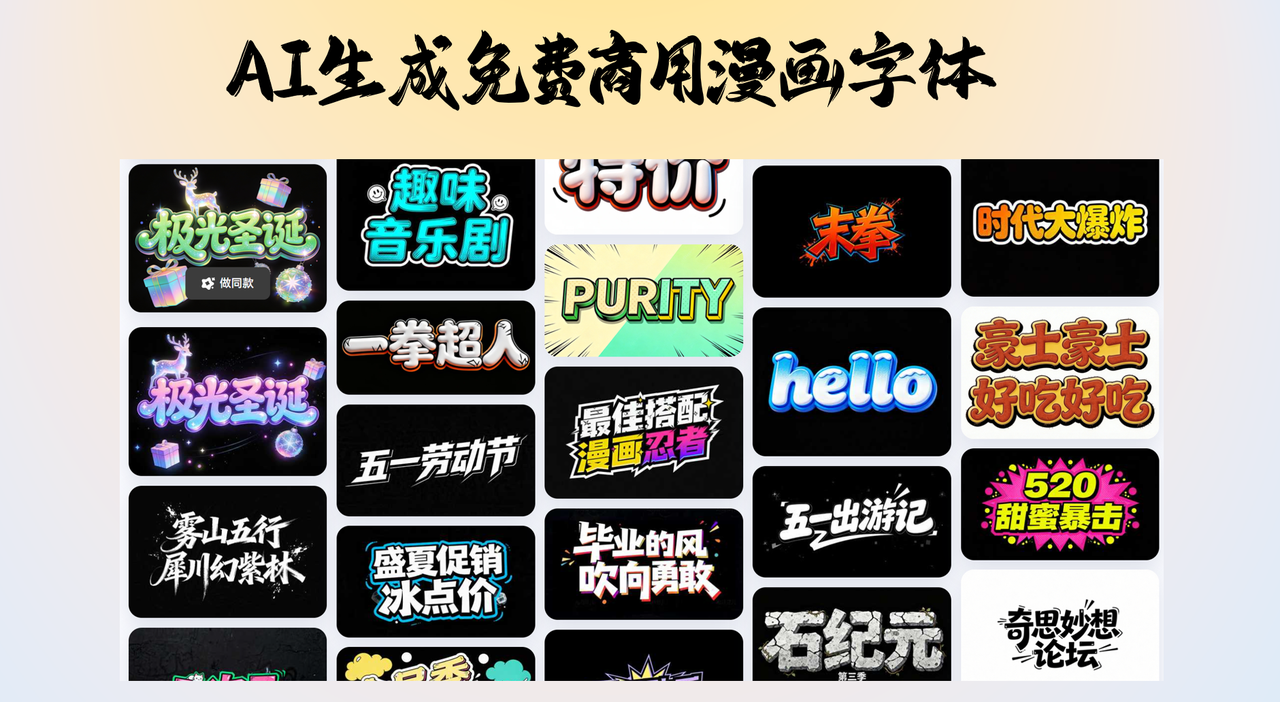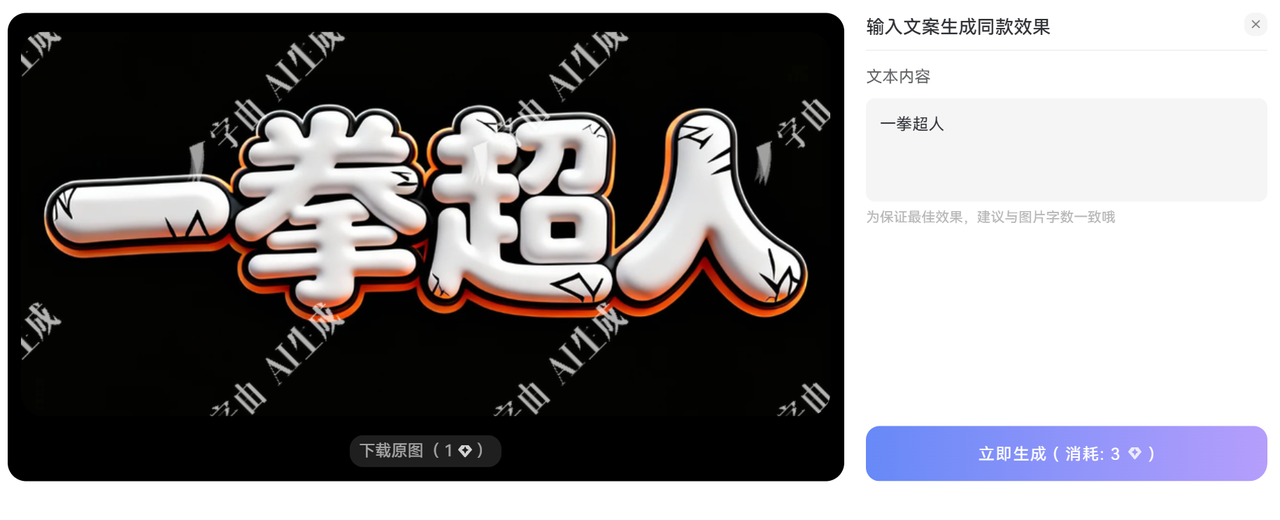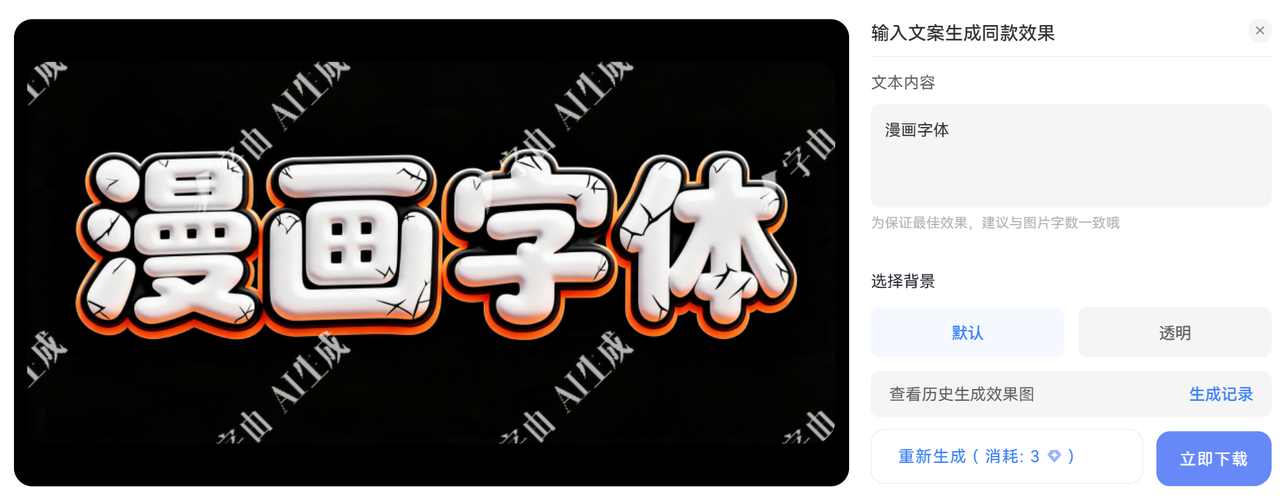
免费商用的漫画字体如何下载,给你分享 AI 生成的方法
做自媒体的朋友,肯定都比较害怕字体侵权。特别是做漫画风格的内容时,这个问题更明显。普通的黑体宋体太死板,但好看的漫画字体又大多收费,免费的那几款用的人太多,作品完全没有辨识度本文就给大家介绍一款既免费商用、又有设计感的漫画字体制作方法。
字由的 AI 字体生成漫画字体
字由推出的 AI 字体设计功能,平台提供丰富丰富的漫画字体模板,你只需要选择自己想要的字体模板,输入自己的文字,就能一键完成漫画字体生成。版权归属清晰,可以放心用于商业项目。
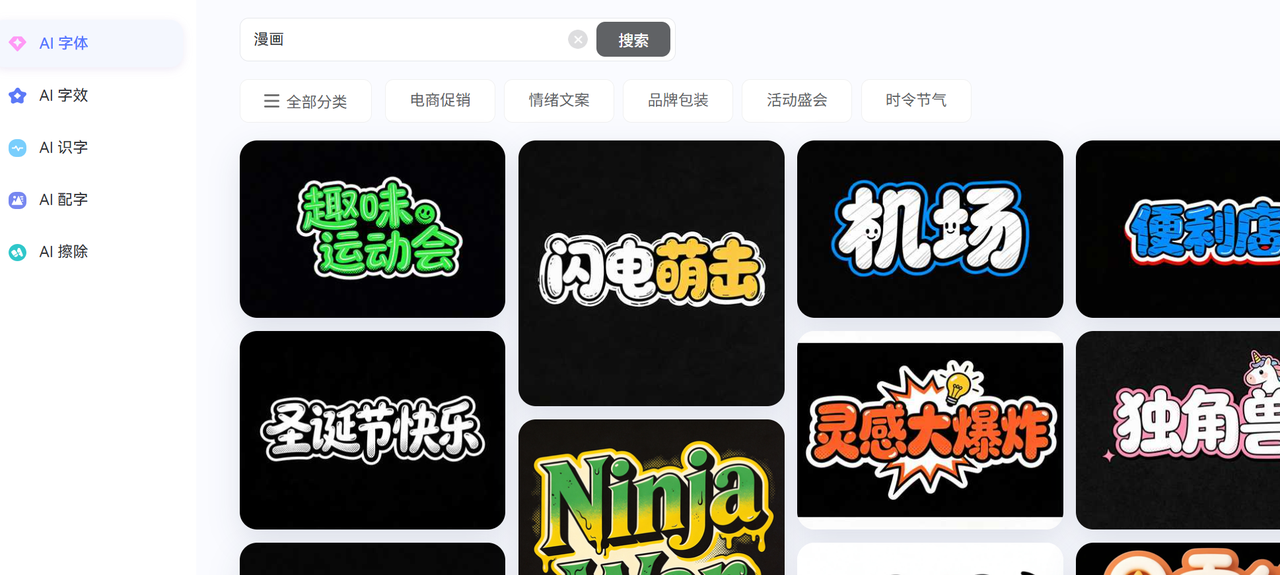
比如我选择了“一拳超人”,这个模板
我这里输入“漫画字体”
整个流程非常简单。打开字由的 AI 字体设计页面后,你会看到一个输入框,直接用中文描述你想要的字体风格就行。如果一次不满意,还可以选择多个模板,进行对比选择。
除了 AI 生成,字由平台还有哪些免费商用字体
在我深入使用字由之后,发现它不仅有 AI 生成工具,本身也是一个非常强大的字体管理平台。平台上收录了大量字体,其中有不少是明确标注可以免费商用的。
我整理了一下自己常用的几款:
- 站酷快乐体:笔画活泼,带有手写感,适合轻松活泼的内容
- 站酷小薇 LOGO 体:字形饱满,识别度高,做 Logo 或者标题很合适
- 思源黑体:虽然不算典型的漫画字体,但调整字重后也能营造出现代漫画的感觉
回想起刚开始做设计时,我花了大量时间在网上找免费商用字体,结果不是链接失效就是授权不明,浪费了很多精力。现在有了字由这样的平台,特别是 AI 字体生成工具出现后,整个流程变得轻松多了。
即便你是新手,刚开始做设计,或者非设计行业的小伙伴,都可以使用AI 生成字体工具,生成免费商用的漫画字体,并且下载到本地使用,简单,便捷,不用担心版权,也能慢慢培养自己的字体审美。